Historyczna czcionka Gutenberga nie była jednym uniwersalnym fontem, tylko gotyckim krojem teksturowym, który miał sprawić, że pierwsze drukowane książki będą wyglądały znajomo dla czytelników przyzwyczajonych do rękopisów. W tym tekście wyjaśniam, czym naprawdę był ten styl, jak go rozpoznać, dlaczego stał się przełomem dla druku i kiedy taki charakter pisma ma sens w nowoczesnym projekcie graficznym.
Najważniejsze fakty o gotyckim kroju Gutenberga
- Nie chodzi o jeden współczesny font, lecz o teksturę, czyli odmianę pisma gotyckiego związaną z wczesnym drukiem.
- Gutenberg użył tego stylu w Biblii 42-wierszowej, bo naśladował wygląd średniowiecznych rękopisów.
- Krój opierał się na gęstym rytmie pionów, ligaturach i skrótach, więc wyglądał ceremonialnie, ale bywał trudniejszy w czytaniu.
- W projektach współczesnych najlepiej sprawdza się w nagłówkach, znakach, opakowaniach i materiałach historyzujących.
- Do długiego tekstu, interfejsów i małych ekranów nadaje się słabo, bo szybko traci czytelność.
- Przy wyborze nowoczesnej wersji liczą się diakrytyki, spacing, licencja i to, czy font nie jest tylko dekoracją bez funkcji.
Czym naprawdę była ta czcionka
Ja zwykle zaczynam od jednego doprecyzowania: nie istniał jeden magiczny „font Gutenberga” w dzisiejszym sensie. Najbliżej prawdy jest tu tekstura, czyli odmiana pisma gotyckiego, znana też jako black letter, użyta w pierwszych drukach związanych z warsztatem Gutenberga. To ważne, bo wiele osób szuka nazwy jednego kroju, a trafia na całą rodzinę historycznych form pisma.
W praktyce chodziło o to, by druk nie wyglądał obco. W połowie XV wieku czytelnik nie miał jeszcze oczekiwania „nowoczesnego fontu”, tylko oczekiwał książki, która przypomina rękopis. Dlatego litery były zwarte, pionowe i mocno rytmiczne, a cały skład miał sprawiać wrażenie gęstej, uporządkowanej faktury. To właśnie z tego powodu temat czcionki Gutenberga jest bardziej opowieścią o typografii niż o samym druku.
Jeśli mam streścić temat jednym zdaniem, to powiedziałbym tak: nie chodzi o ozdobny retro-font, lecz o historyczny język wizualny, który miał nadać drukowi wiarygodność i rangę. Żeby zrozumieć, dlaczego taki język działał, trzeba zobaczyć, jak te litery były zbudowane.
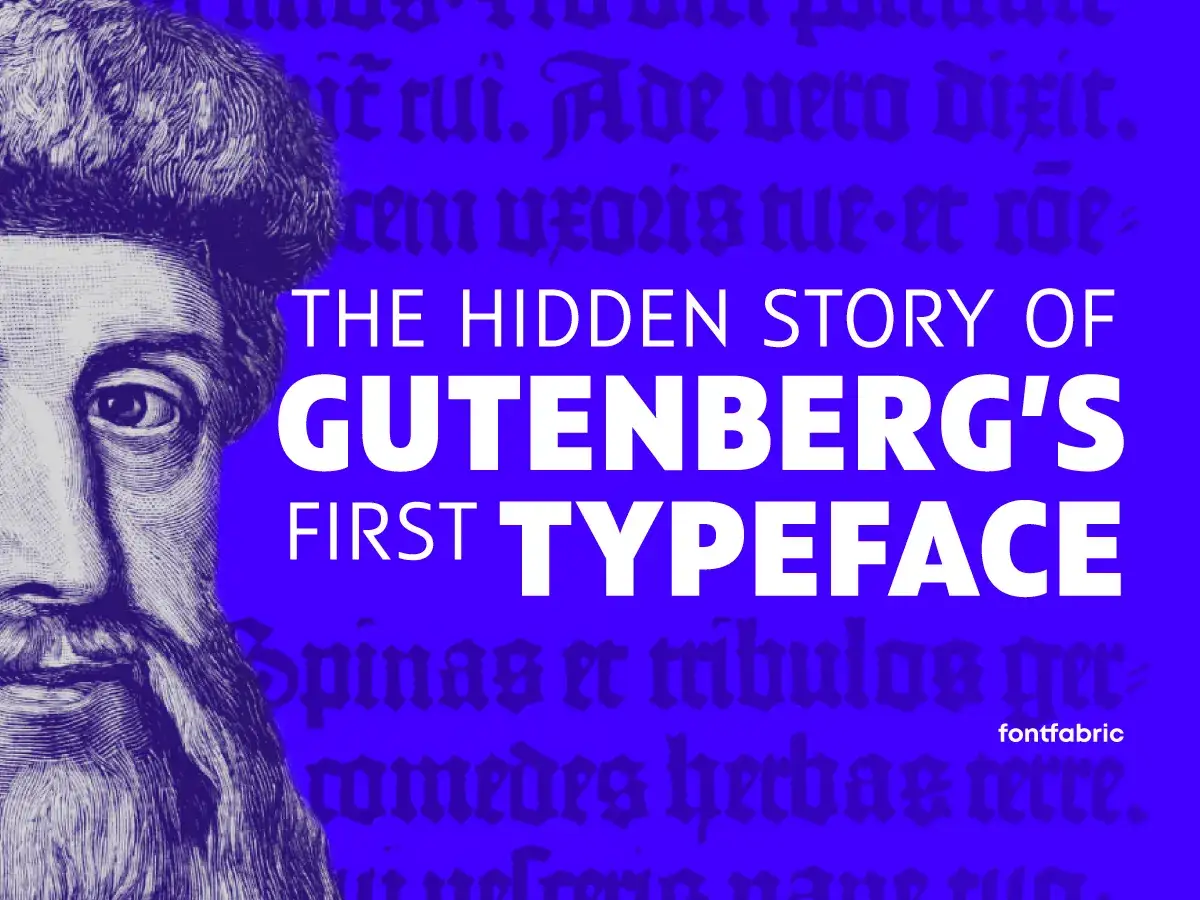
Jak wyglądał styl używany przez Gutenberga
Wczesny krój drukarski Gutenberga był mocno osadzony w gotyckiej kaligrafii. Zamiast miękkich, otwartych kształtów dostajemy pionowy rytm, ostre łamania i bardzo ciasne proporcje. Ten efekt nie był przypadkowy. Gęstość liter miała przypominać ręcznie pisane księgi liturgiczne, a jednocześnie pozwalała zmieścić więcej treści na stronie.
| Odmiana | Jak wygląda | Związek z Gutenbergiem | Gdzie ma sens dziś |
|---|---|---|---|
| Textura | Wąska, pionowa, regularna, z mocnym rytmem | To najbliższa odpowiedź na pytanie o krój kojarzony z jego warsztatem | Rekonstrukcje historyczne, nagłówki, logotypy z tradycją |
| Rotunda | Nieco łagodniejsza i bardziej zaokrąglona | Pokazuje, że gotyk nie był jedną estetyką | Projekty mniej surowe, bardziej humanistyczne |
| Schwabacher | Bliższa ręcznemu pismu, bardziej miękka | Pojawiła się później, więc nie jest „fontem Gutenberga” w ścisłym sensie | Stylizacje regionalne, kraftowe, etykiety |
| Fraktur | Bardzo dekoracyjna, mocno rozpoznawalna | To późniejszy, bardziej znany etap rozwoju blackletter | Znaki, plakaty, akcenty o mocnym charakterze |
W samych drukach z warsztatu Gutenberga nie chodziło tylko o kształt liter. Liczyły się też ligatury, czyli łączenia znaków, oraz skróty typowe dla średniowiecznego zapisu. Dzięki temu strona wyglądała znajomo dla ówczesnego odbiorcy. To właśnie ten miks sprawił, że druk nie był suchą mechaniczną kopią, tylko dobrze zaprojektowanym odpowiednikiem rękopisu. I tu dochodzimy do najciekawszej części całej historii.
Dlaczego ten krój był przełomowy dla druku
Przełom Gutenberga nie polegał wyłącznie na samej możliwości odlewania ruchomych znaków. Równie ważne było to, że nowa technologia została ubrana w estetykę, którą odbiorca już znał. W praktyce oznaczało to mniejszy opór psychologiczny: książka z druku nie wyglądała jak tani substytut, tylko jak przedmiot godny zaufania.
To jest bardzo dobra lekcja także dla współczesnego projektowania. Nowe medium nie zawsze wygrywa tym, że krzyczy „jestem nowe”. Czasem wygrywa dlatego, że potrafi zachować ciągłość i nie zrywa z wyobrażeniem użytkownika o tym, czym dany produkt ma być. Gutenberg zrobił dokładnie to samo z książką. Druk miał być szybszy, stabilniejszy i tańszy, ale wizualnie nie miał zrażać.
Warto też pamiętać, że pierwsze wydania były hybrydą. Część elementów, jak rubryki czy dekoracyjne inicjały, często uzupełniano ręcznie po wydruku. To pokazuje, że typografia nie była wtedy zamkniętym systemem, tylko częścią większego procesu produkcji. Ta lekcja wciąż jest aktualna, zwłaszcza gdy przenosimy historyczny krój do współczesnych projektów.
Gdzie taki styl działa dziś najlepiej
W nowoczesnym designie kroje inspirowane Gutenbergem mają sens wtedy, gdy marka chce mówić o tradycji, rzemiośle, ceremoniale albo historycznym ciężarze. W marketingu to bardzo mocny skrót emocjonalny. Jedno spojrzenie na litery potrafi ustawić odbiór całej marki, bez długiego tłumaczenia.
| Zastosowanie | Dlaczego działa | Największe ryzyko |
|---|---|---|
| Logo i znak marki | Daje autorytet, ciężar i wrażenie zakorzenienia | Może stać się zbyt sztywne albo zbyt „kostiumowe” |
| Etykiety i opakowania | Dobrze buduje klimat rzemiosła, kraftu i limitowanej serii | Łatwo przesadzić z dekoracyjnością |
| Dyplomy, certyfikaty, zaproszenia | Dodaje uroczystości i formalności | W małym rozmiarze traci czytelność |
| Plakaty, wystawy, okładki | Tworzy mocny punkt centralny kompozycji | Konkurencja z innymi ozdobnymi elementami |
Najlepiej działa tam, gdzie krój ma wspierać narrację, a nie prowadzić cały projekt za rękę. Jeśli projektuję materiał użytkowy, nawigację, tekst dłuższy niż kilka zdań albo interfejs, zwykle wybieram coś czytelniejszego. Jeśli jednak potrzebuję wywołać skojarzenie z tradycją, rękodziełem albo instytucjonalnym prestiżem, blackletter potrafi zrobić robotę bardzo szybko. Wybór odpowiedniego kroju to jednak dopiero połowa sukcesu, bo współczesna wersja musi jeszcze dobrze przejść test praktyczny.
Jak wybrać współczesny krój inspirowany Gutenbergiem
Przy wyborze nowoczesnego fontu nie patrzę wyłącznie na to, czy wygląda „staro”. To za mało. Dobry krój inspirowany teksturą musi jeszcze działać po polsku, w różnych rozmiarach i na różnych nośnikach. W projekcie komercyjnym liczy się nie tylko klimat, ale też użyteczność.
| Na co patrzeć | Dlaczego to ważne | Jak sprawdzić szybko |
|---|---|---|
| Polskie znaki | Bez nich font może wyglądać efektownie, ale być nieużywalny | Przetestuj ą, ę, ł, ń, ó, ś, ź, ż w nagłówku i w nazwie marki |
| Odstępy między literami | Blackletter żyje rytmem, a zły spacing psuje cały efekt | Sprawdź wersję w małym i średnim rozmiarze |
| Ligatury i alternatywy | Dają charakter bez sztucznego przerysowania | Otwórz panel OpenType i zobacz, co naprawdę oferuje font |
| Licencja | W projekcie komercyjnym to kwestia bezpieczeństwa | Upewnij się, że licencja obejmuje użycie w logo, druku i webie |
| Czytelność w małej skali | To zwykle najsłabszy punkt ozdobnych krojów | Wydrukuj próbkę i sprawdź, co dzieje się przy 12-16 px |
W praktyce dobrze działają dwa typy wyboru: albo sięgasz po wierniejszą rekonstrukcję tekstury, gdy projekt ma wyraźnie historyczny charakter, albo po luźniejszą inspirację blackletterem, jeśli potrzebujesz tylko emocjonalnego akcentu. Ja zazwyczaj odradzam fonty, które są jednocześnie zbyt udziwnione i zbyt słabo opracowane technicznie. Taki wybór wygląda efektownie tylko na zrzucie ekranu, a w realnym projekcie szybko zaczyna przeszkadzać. I właśnie tutaj pojawiają się najczęstsze błędy.
Błędy, które najczęściej psują efekt
Największy problem z takimi krojami polega na tym, że łatwo potraktować je jak samodzielną dekorację. To błąd. Czcionka inspirowana Gutenbergiem działa tylko wtedy, gdy ma kontekst. Bez niego robi się z niej przypadkowy kostium, a nie świadomy element identyfikacji.
- Używanie jej w długim tekście - wygląda szlachetnie przez chwilę, ale męczy czytelnika bardzo szybko.
- Łączenie z drugim ozdobnym fontem - zamiast hierarchii powstaje wizualny hałas.
- Zbyt mały rozmiar - cienkie szczeliny i gęste formy zlewają się w jedną plamę.
- Brak światła wokół liter - taki krój potrzebuje oddechu, inaczej traci rytm.
- Udawanie historyczności na siłę - jeśli projekt nie ma związku z tradycją, efekt bywa sztuczny.
Warto też uważać na nadmiar pogrubień i agresywnych efektów. W blackletterze siła znaku bierze się głównie z konstrukcji liter, nie z mechanicznego dokręcania ciężaru. Im mniej przypadkowych modyfikacji, tym większa szansa, że krój zachowa swój charakter. Gdy to zrozumiesz, łatwiej odróżnisz dobry wybór typograficzny od samej stylizacji.
Co zostaje z gotyckiego kroju, gdy przeniesiesz go do współczesnej marki
Jeśli mam zostawić po tym temacie jedną praktyczną myśl, to taką: najważniejsza nie jest sama egzotyka liter, tylko decyzja, po co one w ogóle mają się pojawić. W projektach marketingowych taki krój potrafi dodać marce autorytetu, rzemieślniczego charakteru i poczucia ciągłości. Użyty bez celu robi dokładnie odwrotnie, bo zamienia się w ozdobę bez treści.
Dlatego patrzę na ten styl jak na mocny akcent, a nie uniwersalne rozwiązanie. Właściwie dobrany krój historyczny potrafi podnieść rangę projektu w kilka sekund, ale tylko wtedy, gdy wspiera narrację, czytelność i kontekst. Wtedy działa najlepiej, bo przypomina o tym, co Gutenberg zrobił najważniejszego: połączył technologię z czytelnym, przekonującym obrazem książki.